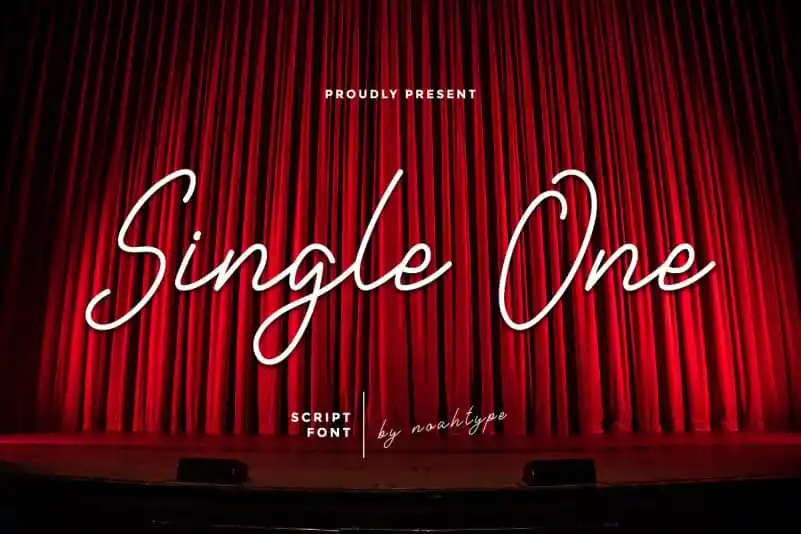
Single One Handwriting Font – Download Grátis
A Single One Handwriting Font é uma elegante fonte para escrita a mão com estilo moderno e simples. Cada linha desta fonte foi cuidadosamente elaborada em cada pequena marcação, projetada para parecer como possível próximo de uma script a mão real, permitindo combinações perfeitas nas letras individuais. Se você deseja um ‘s’ que se mistura com o ‘t’, encontrará isso na ligatura de letra ‘st’. Esse script é ideal para quem precisa de elegância e estilo em seus designs. Esta fonte foi criada para aqueles que valorizam a naturalidade do design, oferecendo uma impressão livre como se fossem escrever por si próprios. Não apenas combinações de letras se tornam mais naturais, mas também há um toque fluido e espontâneo em seu uso, garantindo uma aparência tão autêntica quanto possível. Com a Single One Handwriting Font, você pode transformar qualquer texto em escrita a mão com uma textura real e única.
Designer: noahtype